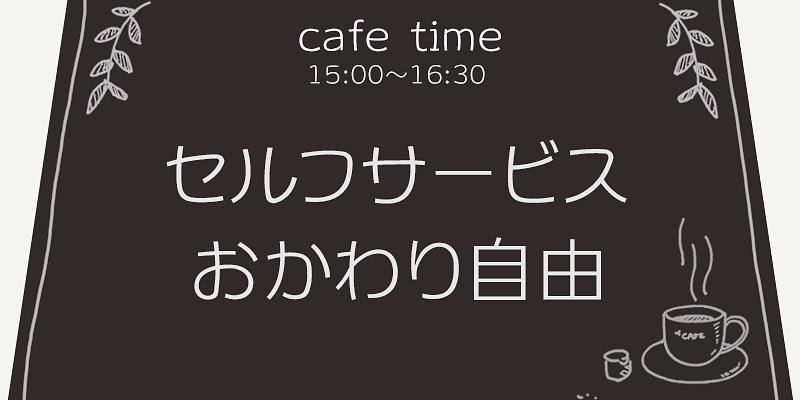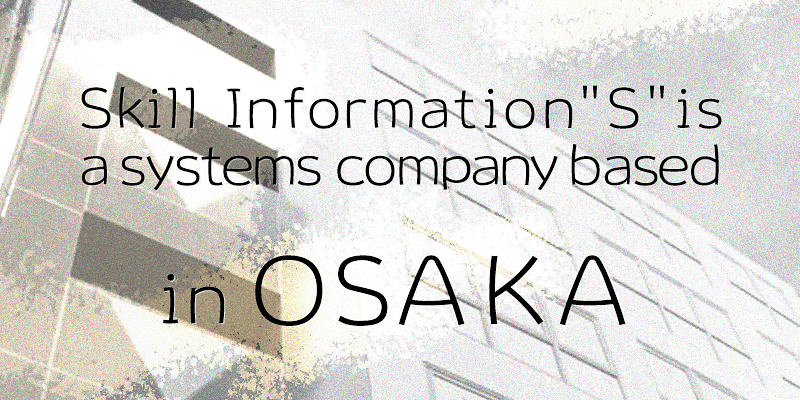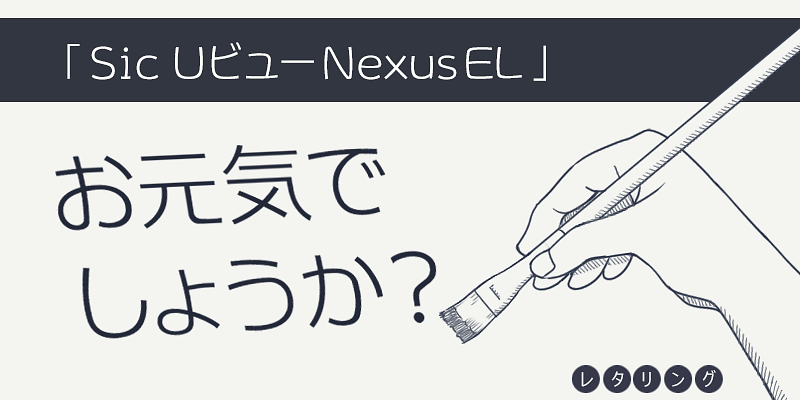
El difunto Takeharu Suzuki usó su amplia experiencia, que abarcaba desde rotulación hasta fuentes de mapa de bits, fuentes para procesadores de texto y a pincel, para crear sus fuentes. En particular, se centró en la búsqueda de un tipo de letra gótico relajado para texto horizontal, lo que contribuyó al desarrollo del diseño de alta legibilidad de la fuente estándar Meiryo.
La diversidad de sus diseños de letras abarca no solo las cálidas tipografías manuscritas a pincel y las básicas, sino también, en general, las góticas, estilizadas y de exhibición. Sus tipos de letra se pueden usar en una gran variedad de aplicaciones, que incluyen publicidad, vídeos y contenidos digitales. Aportan una sensación de originalidad y tienen una gran valoración.
Conocida por su enfoque en el desarrollo de software, en particular para el sector de servicios sanitarios, Skill Information “S” acabó en el sector de las fuentes por medio de una colaboración con Techno Advance Co, Ltd, en 2007.